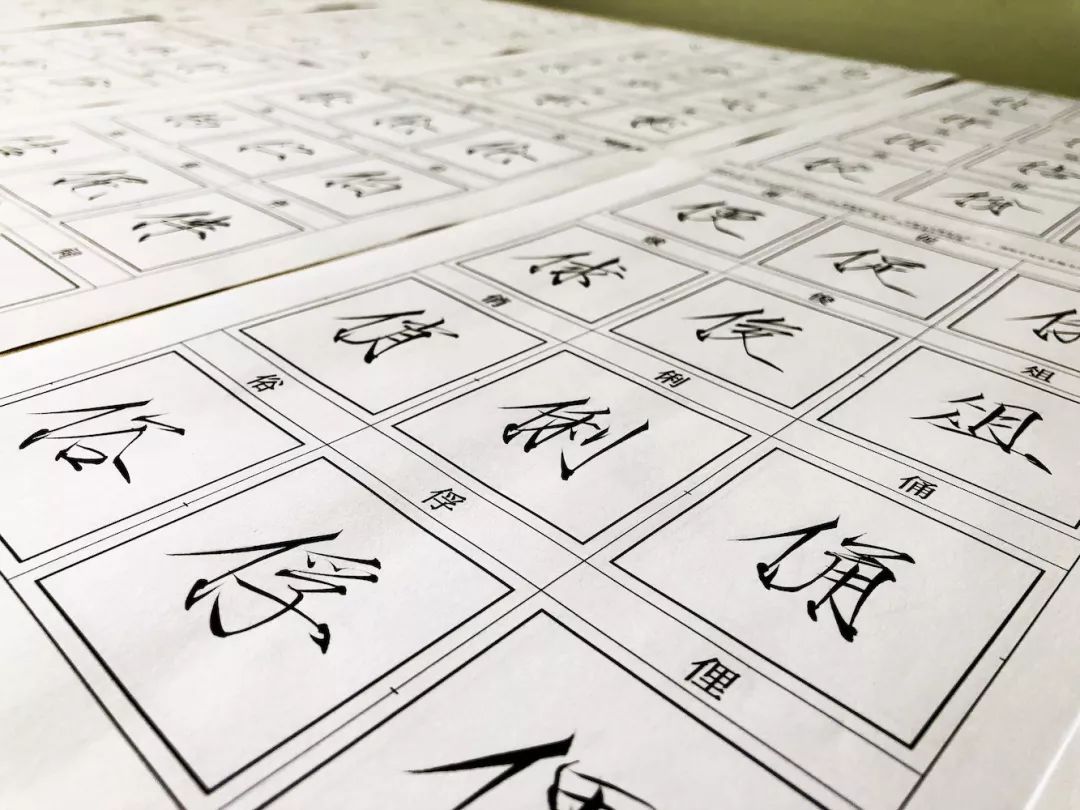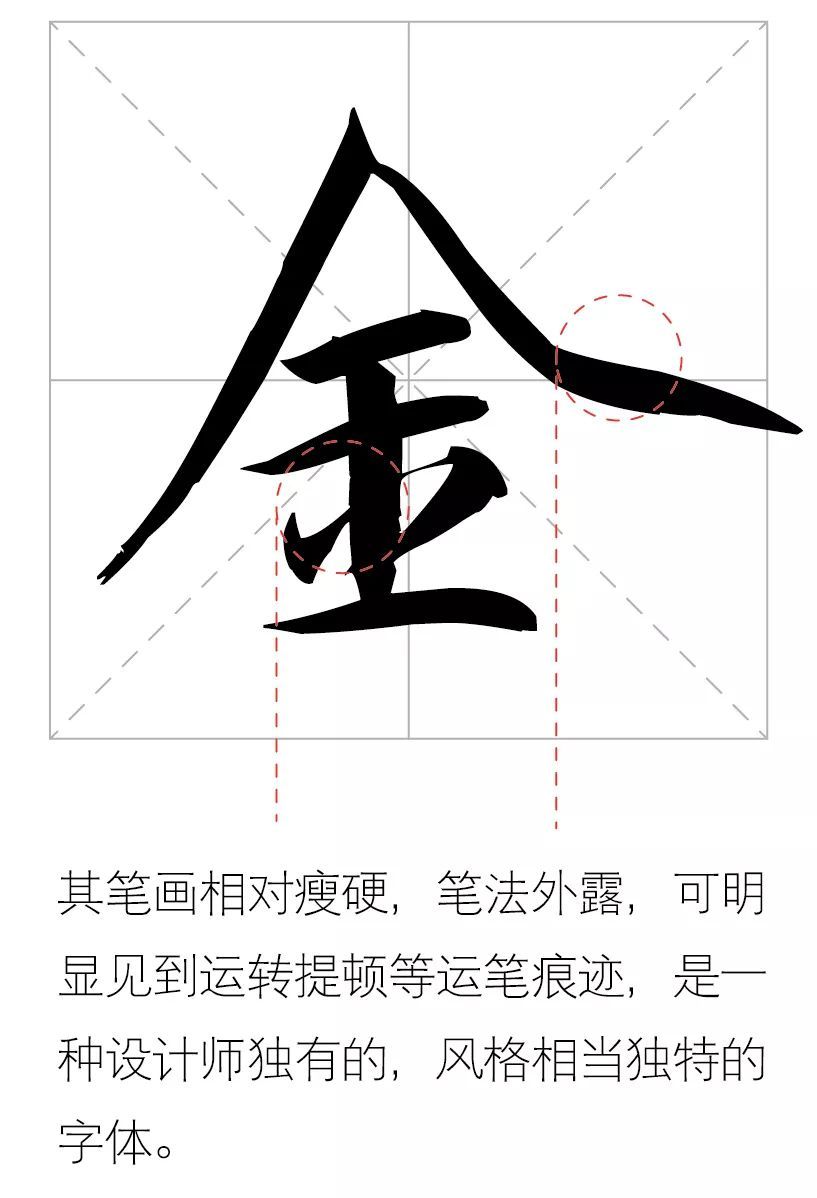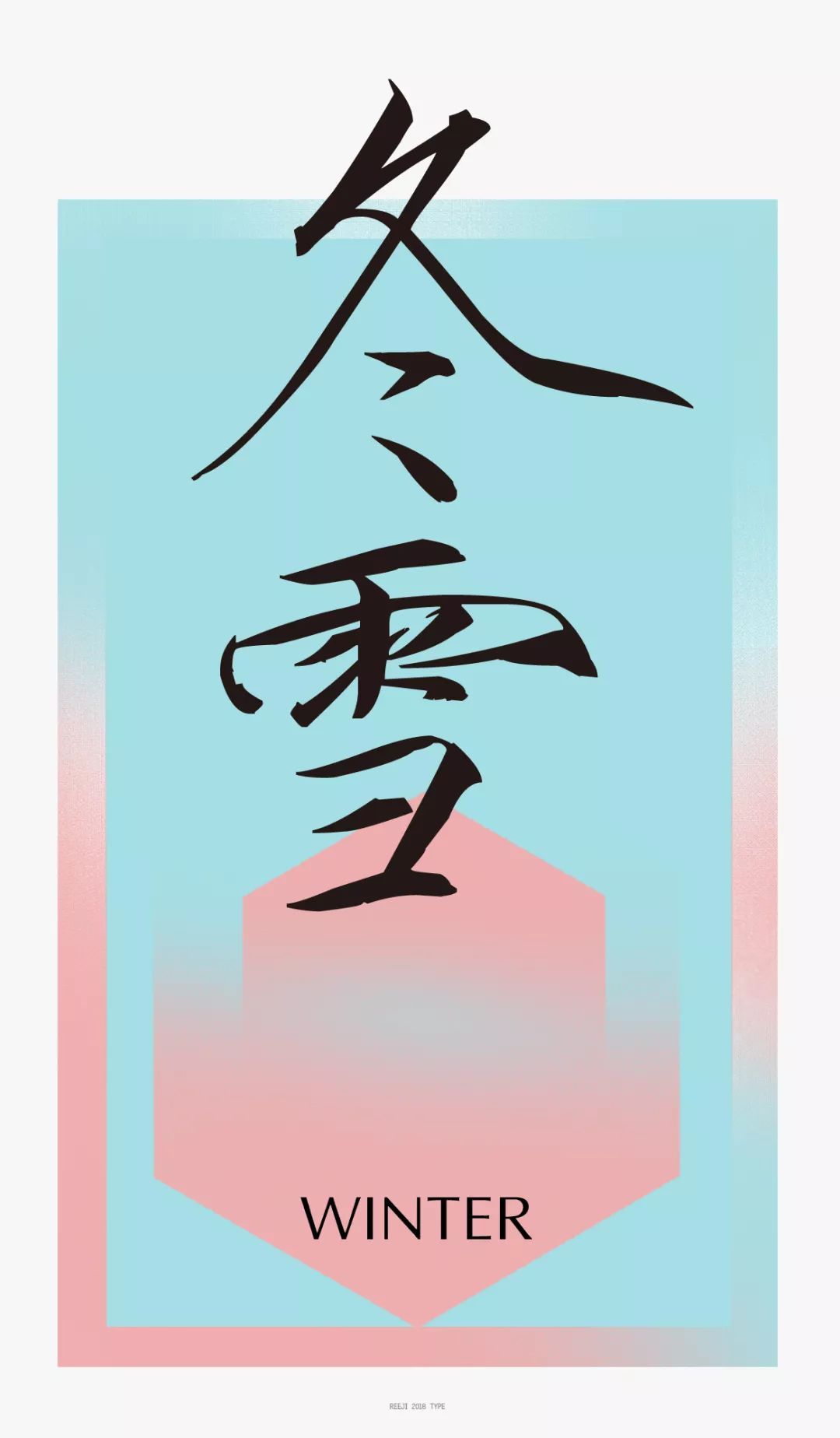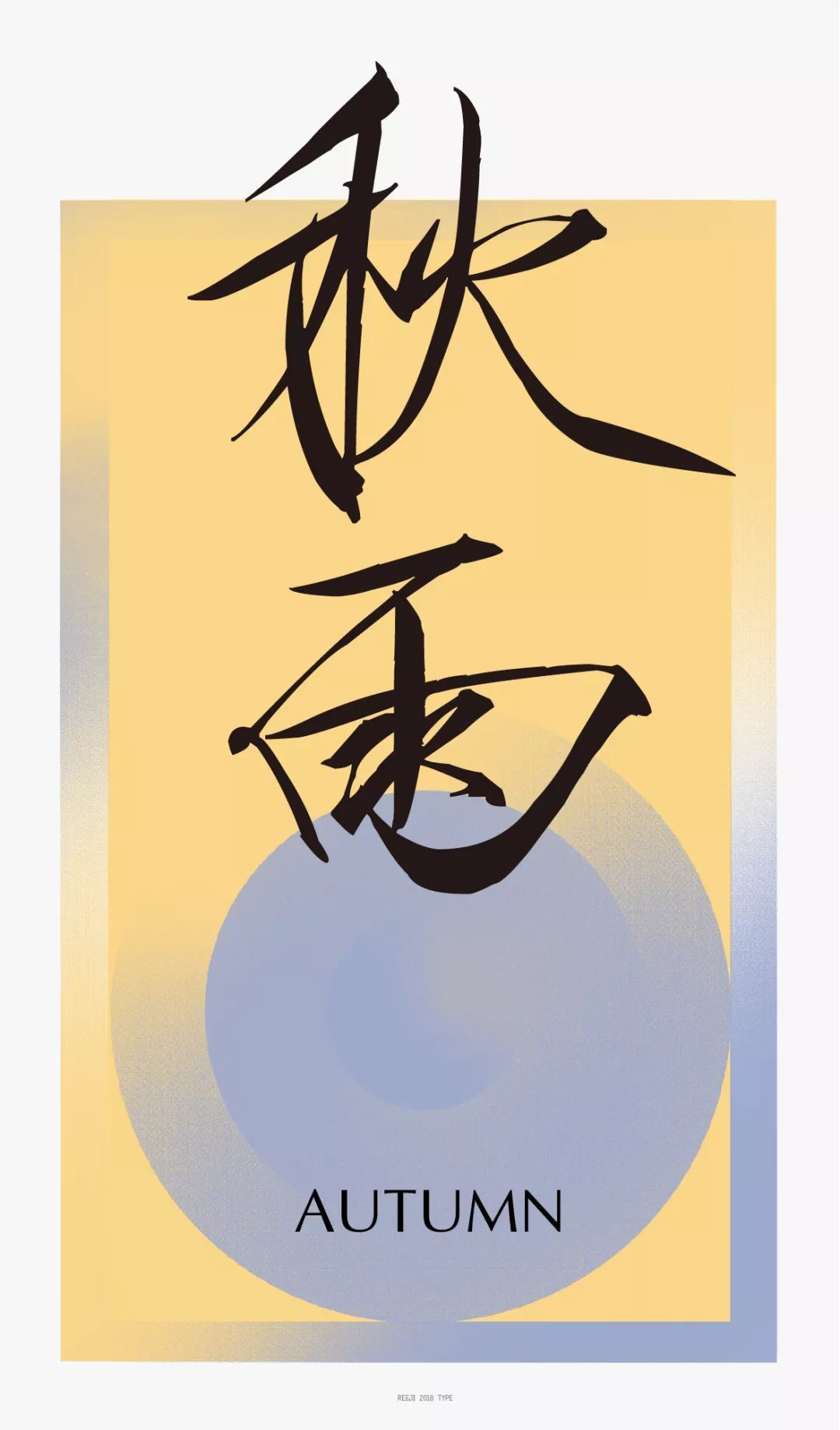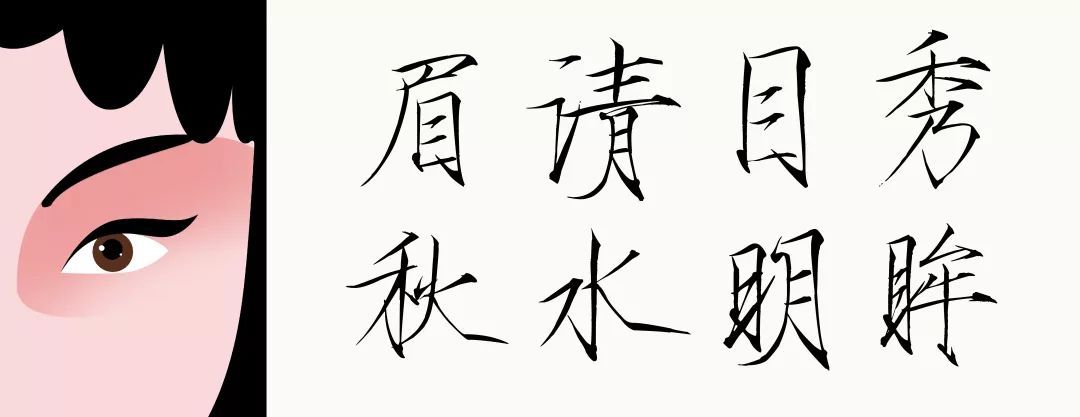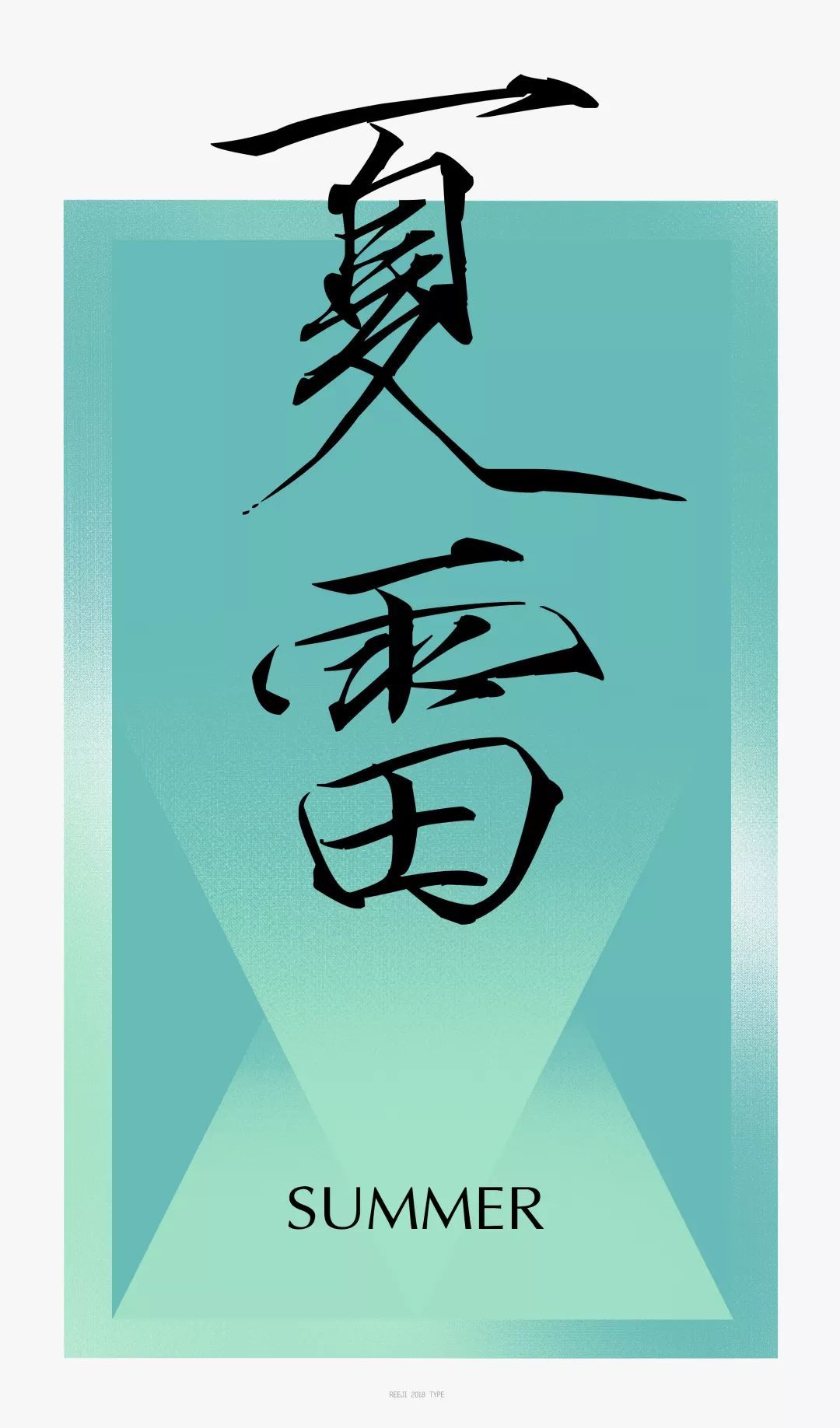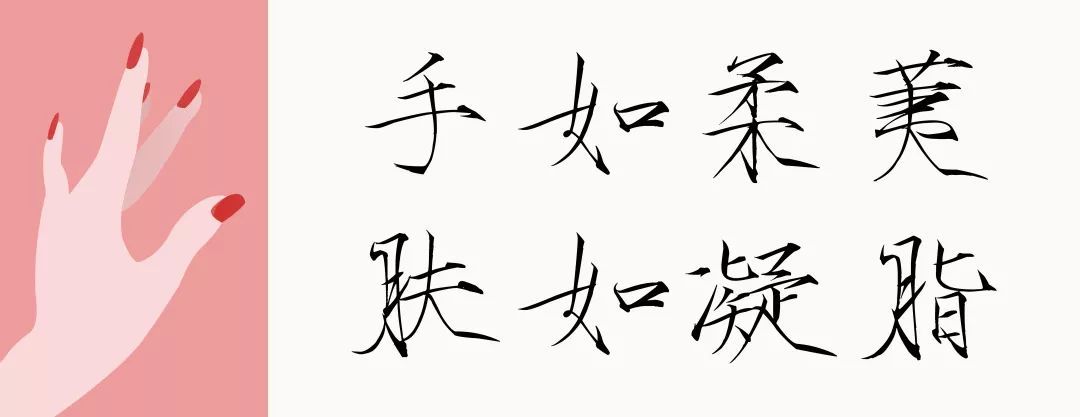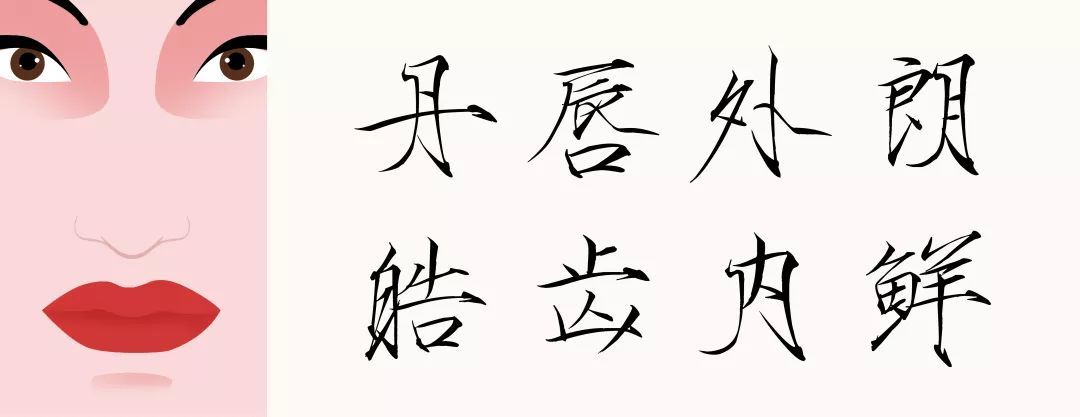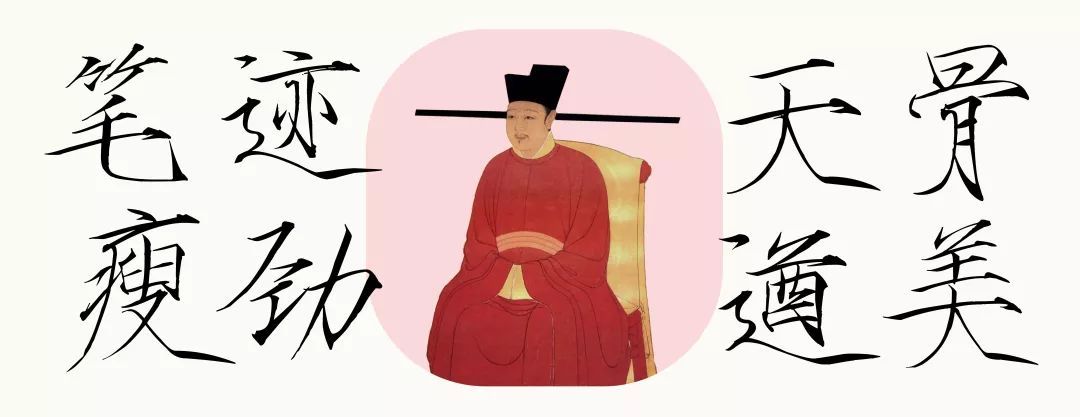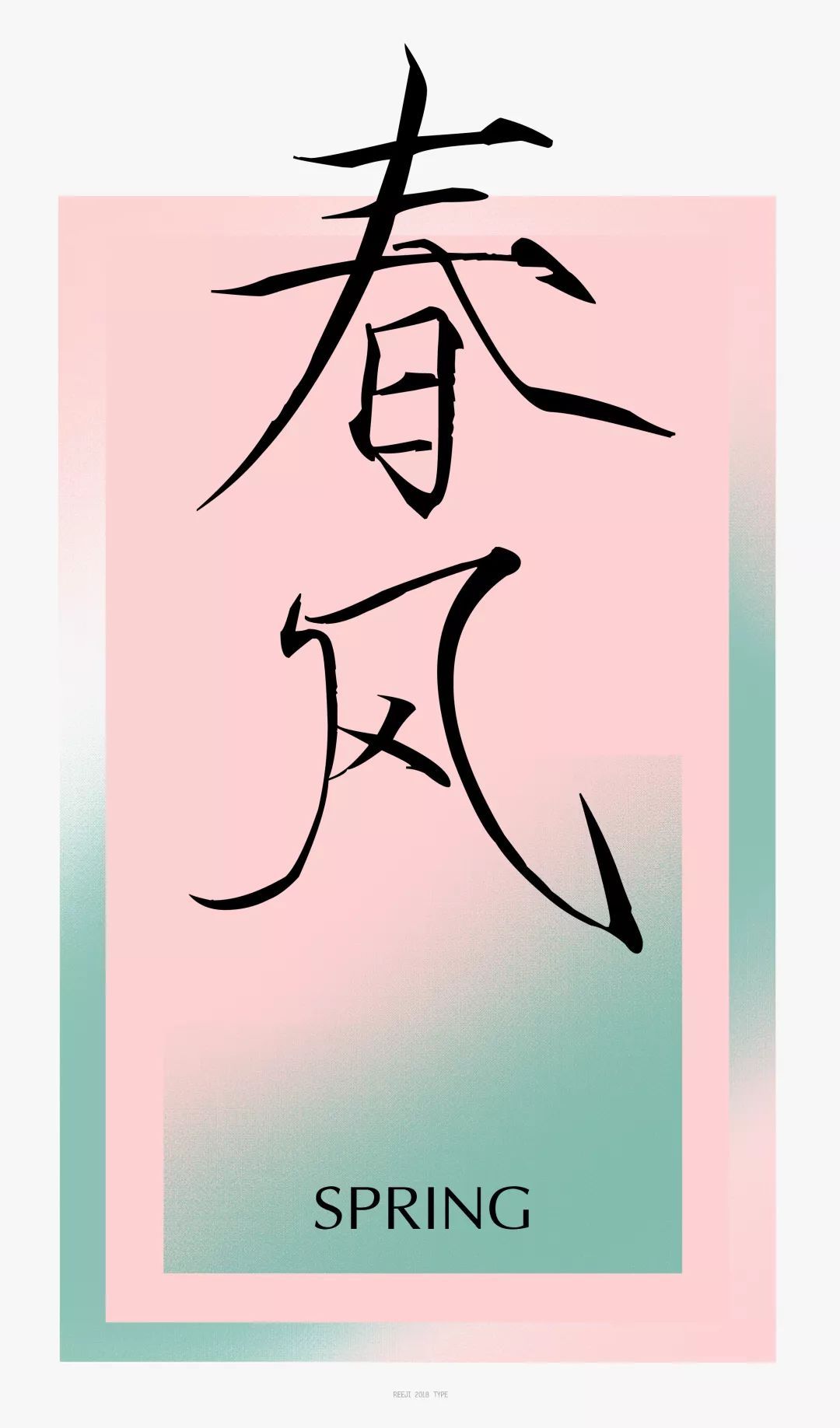
龙书法杨永志瘦金体|仙风鹤韵的宋代风骨
赵佶,一个毁誉参半的君王,他登峰造极的审美造诣与风流尚意的书法修养,隔着九百年的烟尘与风雨,被世人偏爱着。他一生辉煌的艺术创造中,最了不起的是开创了中国书法史上前无古人的艺术宝藏——瘦金体。
复刻宋代遗风
瘦金体其名如雷贯耳,听起来就激越动人,笔锋如刀屈金断玉,撇如匕首、捺如兰叶,联笔如仙鹤行空舞,清癯优美间充斥着凛凛风骨,备受后人推崇。
龙书法杨永志瘦金体沿袭赵佶重韵尚意的文人风骨与书法策略风格,在原有瘦金体的笔划和结构上进行了调整,融入现代审美风尚,创作的一款独具宋代风韵的书法瘦金体,分为正楷与行楷两种字形,丰富应用范围。
01
行笔如鹤
龙书法杨永志瘦金体承袭宋徽宗的鹤韵,将鹤的肢体、鹤的姿态糅合在笔画间,用笔中长横的收笔、竖的顿笔及其转折处似有“坠尾”、“鹤膝”,笔画到处显现着鹤颈与鹤足的细筋之感。
02
兰捺竹姿
撇脚形态特别,每一个撇捺,仿佛看到了兰叶的优雅风姿。那舒展开张的结体,左右款摆,恍若空谷幽兰,自有一番清冷美丽。起笔出锋较多,露锋行笔,撇画结束时不做任何藏锋处理,似竹的挺拔俊秀,点捺横折间如若竹叶翩飞,肃杀之气弥漫。
03
拉弓放箭
因宋徽宗擅长工笔画,更喜欢硬笔之弹力.故瘦金体线条如张弓之弦。其形曲折,其势迅捷.其意则踌躇曼妙。书画两种艺术的融合、互借,构成了瘦金体的特有艺术张力,使其既有工笔细描之婉转纤细,又有金戈铁马气吞山河的万钧之力。
04
现代演绎
极具古韵与审美风尚的龙书法杨永志瘦金体,颇受现代文化市场喜爱,可应用于现代美术/艺术馆/文创产品/影视海报/印刷等多种场景。